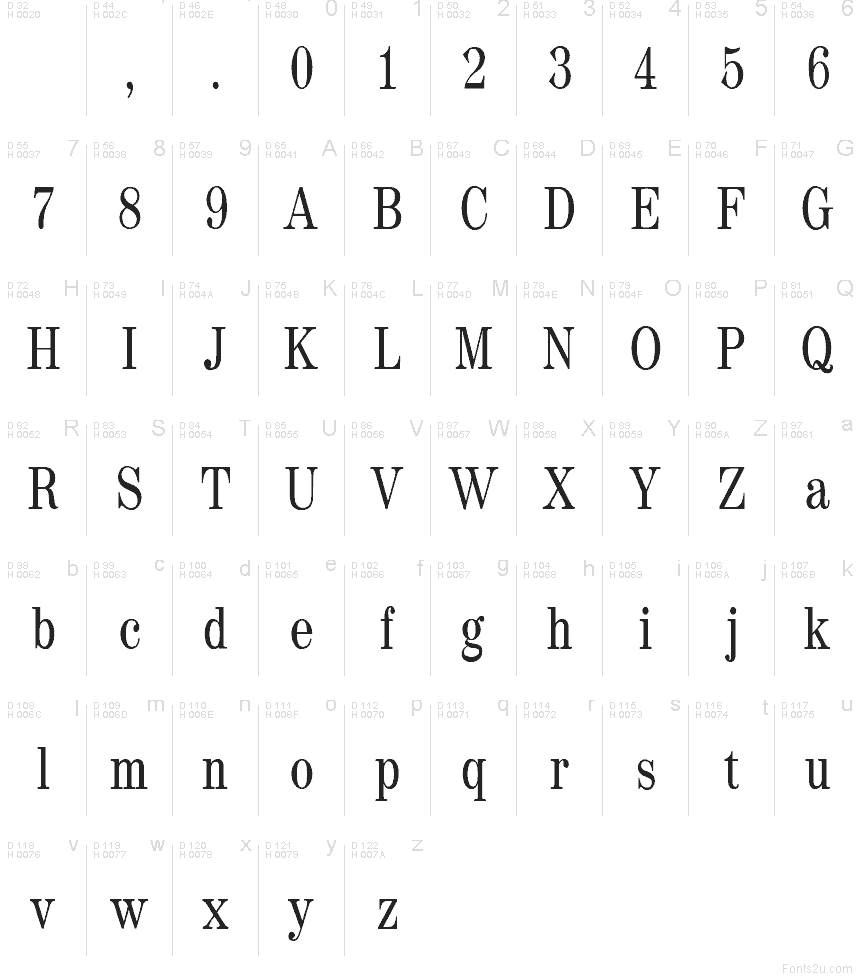
Wildest-Regular
Wildest, de Gholib Tammami, es una tipografía serif con alto contraste que destila un aire editorial y de moda. Sus letras combinan trazos verticales gruesos con uniones muy finas y remates nítidos y afilados, otorgando a la fuente un ritmo dramático que se siente elegante, no recargado.
Es ideal para cabeceras de revistas, packaging de cosmética, branding de boutiques, portadas de libros y titulares de pósteres donde un toque de contraste marca la diferencia. Al ser una fuente gratuita, Wildest también encaja en tarjetas de título y textos cortos, especialmente si buscas ese estilo moderno-clásico y elegante donde la nitidez de los remates se convierte en la protagonista de la composición.